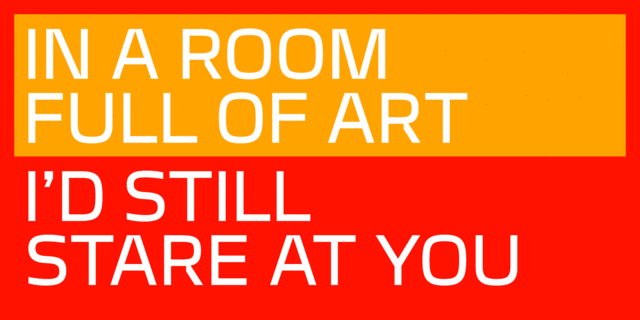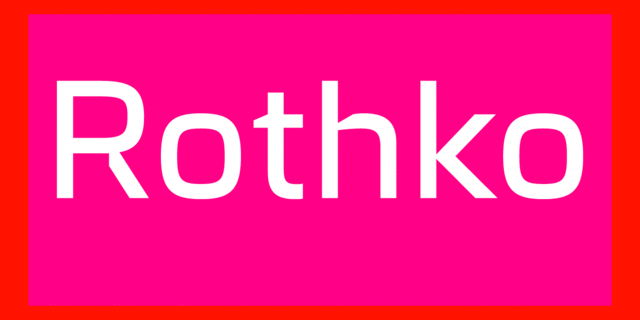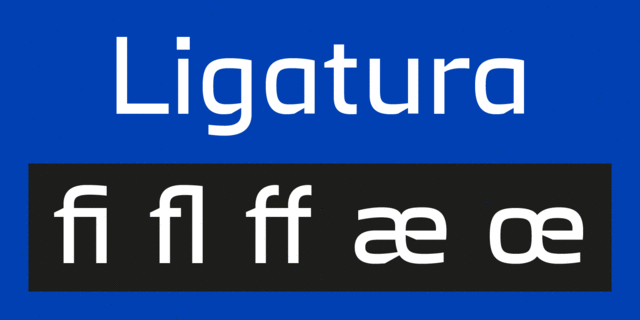
Rothko – крепкий, статичный гротеск. Округлые формы стремятся к квадрату. Плавный силуэт букв контрастирует с чётким ритмом набора. Ярким акцентом выступают места соединение диагональных штрихов. Шрифт содержит стандартный набор латиницы и кириллицы, математические символы, стандартные лигатуры, а также лигатуру для украинской пары «її». Rothko предназначен для плакатных слоганов и ярких заголовков. Шрифт разработал Алексей Поповцев в 2018 году.
лаконичный, космический, техногенный, футуристичный, инженерный, чертежный, точный, ровный, убедительный, прямоугольный, стабильный, твердый, серьезный, надежный, уверенный, сильный, устойчивый, индустриальный, статичный, практичный, прагматичный, техничный, урбанистичный, грубый, качественный, крепкий, логичный, городской, современный, гладкий, машинный, железный, стальной, резкий, четкий, кинематографичный
инновации, техника, прибор, фантастика, космос, наука, интернет, мобильная связь, гаджет, девайс, айтишник, айти, IT, технологии, коворкинг, инженер, промышленность, станок, инструмент, электростанция, энергетика, завод, ремонт, блокбастер, боевик, экшен, игра, шутер, дизайн, город, транспорт, навигация, конструктор, робот, чертеж, электроника, машина, автоматика, автомобиль, урбанистика, мотор, двигатель, андроид, железо, рентген, кино, киберспорт, компьютерная игра Стилистика: